Možná se vám někdy stane, že se v diskuzi na internetu dozvíte, že jste úplně mimo, když používáte slovo FONT. A v podstatě bude mít kritik pravdu.
Arial není font.
Calibri také není font.
Ani Georgia není font.
Arial je písmo, Calibri také a Georgia jakbysmet. Ale nejsou to fonty.
Kdy se tedy používá slovo FONT?
Pojďme se vrátit trošku do historie. Do tiskařské dílny v 15. století…
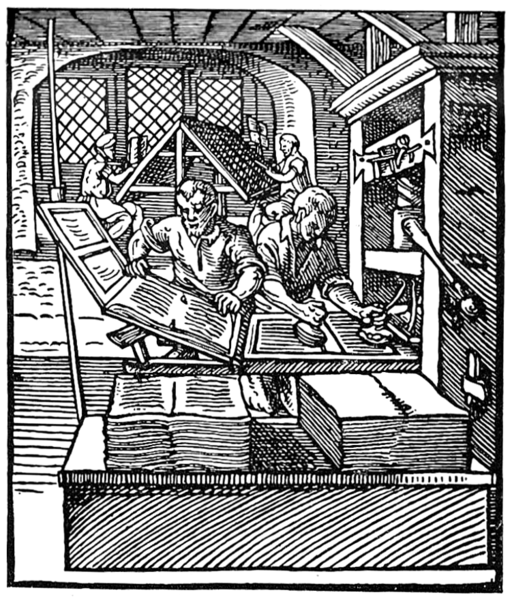
Byla plná polic s různými sadami písma. Každé písmenko (litera) bylo odlité v kovové podobě. Těch podob bylo mnoho, protože když jste chtěli to samé písmenko použít v jiné velikosti, nemohli jste kliknout na tlačítko „Velikost 42“. Použili jste jiný odlitek. Stejná výška písmen, umožnila skládání písmen vedle sebe ve slova, ve věty, v odstavce a ve stránky.
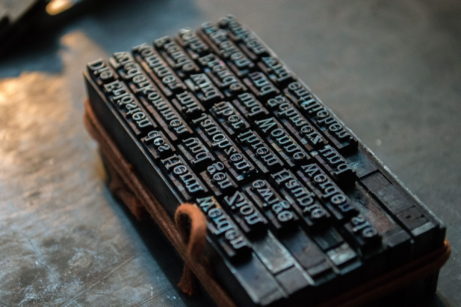
Bylo to řemeslo se vším všudy. Každá abeceda měla kromě písmen i zdvojené litery, mezery a interpunkci. Každou stranu poskládal sazeč do dřevěného rámu, sazebnice. Měla své místo pro obrázky i pro mezery. Měla svůj řád.
Pointa mého vyprávění je v tom, že kdyby chtěl Gutenberg svou bibli vytisknout v patkovém Times New Roman (používal samozřejmě úplně jiné písmo, ve 14.století zřejmě gotickou Texturu), nepoužil by jeden jednu sadu písma Times New Roman, ale musel by použít pro každou velikost a každý řez jinou sadu písmen. *
- Pro nadpisy Times New Roman velikosti 20px.
- Pro text Times New Roman velikosti 11px.
- Pro citace Times New Roman velikosti 11px a řez kurzíva.
Pro nadpisy, text i citace by použil pokaždé jiný font. Rovná se, jinou sadu písmen.
Font je kompletní sada znaků abecedy jedné velikosti a jednotného stylu.
Takže pokud bychom používali původní terminologii tiskařů, slovo font můžeme použít v případě, kdy jasně definujeme i velikost a řez použitého písma.
Prostě FONT je jako když chcete boty Adidas, vzor 15, v bílé barvě s červeným pruhem a velikost 38, nestačí říct „Adidasky“.
Uklidním vás, v současnosti i spousta známých typografů používá veřejně slovo font, stalo se téměř synonymem pro „písmo“ a upozorňování na špatné použití slova font vnímám spíš jako projev „teď vám to nandám“.
Běžně však používáme slova „font“ a „druh písma“ nerozlišeně. Existují horší hříchy.
Simon Garfield
A víte co? Když už jsme u těch výletů do historie, pojďte si udělat ještě jeden. Tentokrát lingvistický.
Miluju lingvistiku, byly to mé nejoblíbenější hodiny francouzštiny na vysoké škole, a chybí mi to noření se do hloubi jazyka a sledování červené nitě v používání slova až k prapůvodnímu významu. Nevěřili byste, kolik slov (nejen) v češtině pochází právě z francouzštiny.
Co znamená slovo FONT?
První verze zní, že slovo FONT do Anglie přišlo z francouzštiny, zřejmě díky Vilému Dobyvateli, ve francouzském slově „fonte“, které se dá přeložit jako „tavit“ nebo „slévat“. Sloveso fondre znamená roztavit, rozpustit. A protože fonte se dá přeložit jako slévat dostáváme se ke krásnému českému slovu písmolijectví. K nádherně zvukomalebné písmolijně.
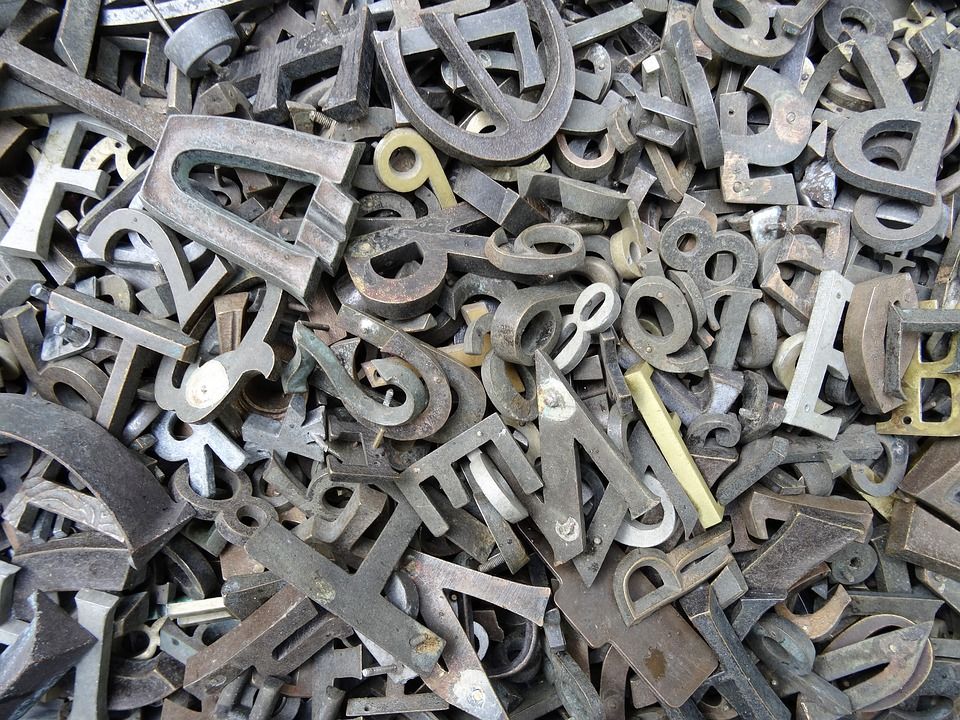
Písmo jako zdroj vědění
Druhá verze je romantičtější a má oblíbená. Z anglického slova „fount“ – pramen, můžeme vnímat písmo jako zdroj vědění. Co jiného je písmo, než studnice vědomostí a pramen poznání? V češtině můžeme slovo fount přeložit jako fontána a asi už tušíte pozadí, proč jsem ze všech nápadů na název pro Newsletter vybrala právě Fontánu.
„Čtenáři budou úspěšní ve světě umění a věd, pokud budou respektovat „tuto neustále prýštící studnici“…“
Proslov matematika Lucy Pacioli v Benátkách roku 1508 (z knihy To je můj font)
Takže už víme, co je to font.
Každý řádek v následujícím obrázku je vlastně jeden font.
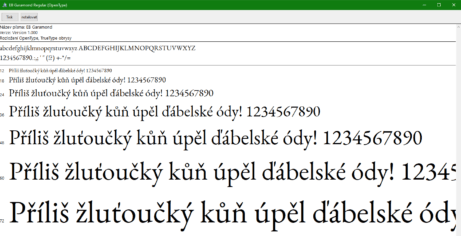
Ale to není vše, může mít jednu velikost, ale stačí, když se změní řez a voilà, už je to zase jiný font.
Řez fontu
Třeba taková Georgia může mít více podob. Kromě klasické Georgie může mít krásnou kurzívu (Italic), může být tučná (Bold) a dokonce i tučná kurzíva (Bold Italic).
Tomu se říká řez písma.
A pokud se stane, že si nenainstalujete řez Italic (neboli kurzíva) a snažíte se změnit písmo na kurzívu kouzelným tlačítkem v liště , právě jste udělali pěkné typografické faux-pas.
Kurzíva neznamená, že řez nakloníte, ale typograf ji vytvoří, jako plnohodnotný řez, který může mít stejné proporce, ale jiné tvary. A pokud písmo kurzívu nemá, tak ji typograf z nějakého důvodu nevytvořil a není důvod používat kurzívu falešnou.
Pokud písmo nemá řez kurzívu, tak ho žádným tlačítkem nevytvoříte, ale jenom nakloníte klasický řez. Podívejte se, jaký je to rozdíl.
- Jednička je klasický řez.
- Dvojka řez kurzíva.
- Trojka „falešná“ kurzíva.
Písmo může mít daleko více řezů, než jenom bold a italic, třeba i kapitálky, řez light, thin, semibold, atd. Například font Roboto:
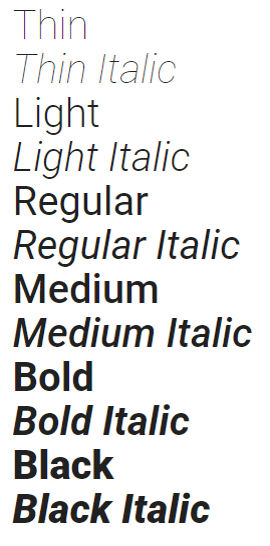
Na světě je víc než 100 000 fontů. Pojďme si je užít!
* ve skutečnosti použil Gutenberg téměř 300 různých písmen.